Семейная книга рецептов: рукописный шрифт и читаемость
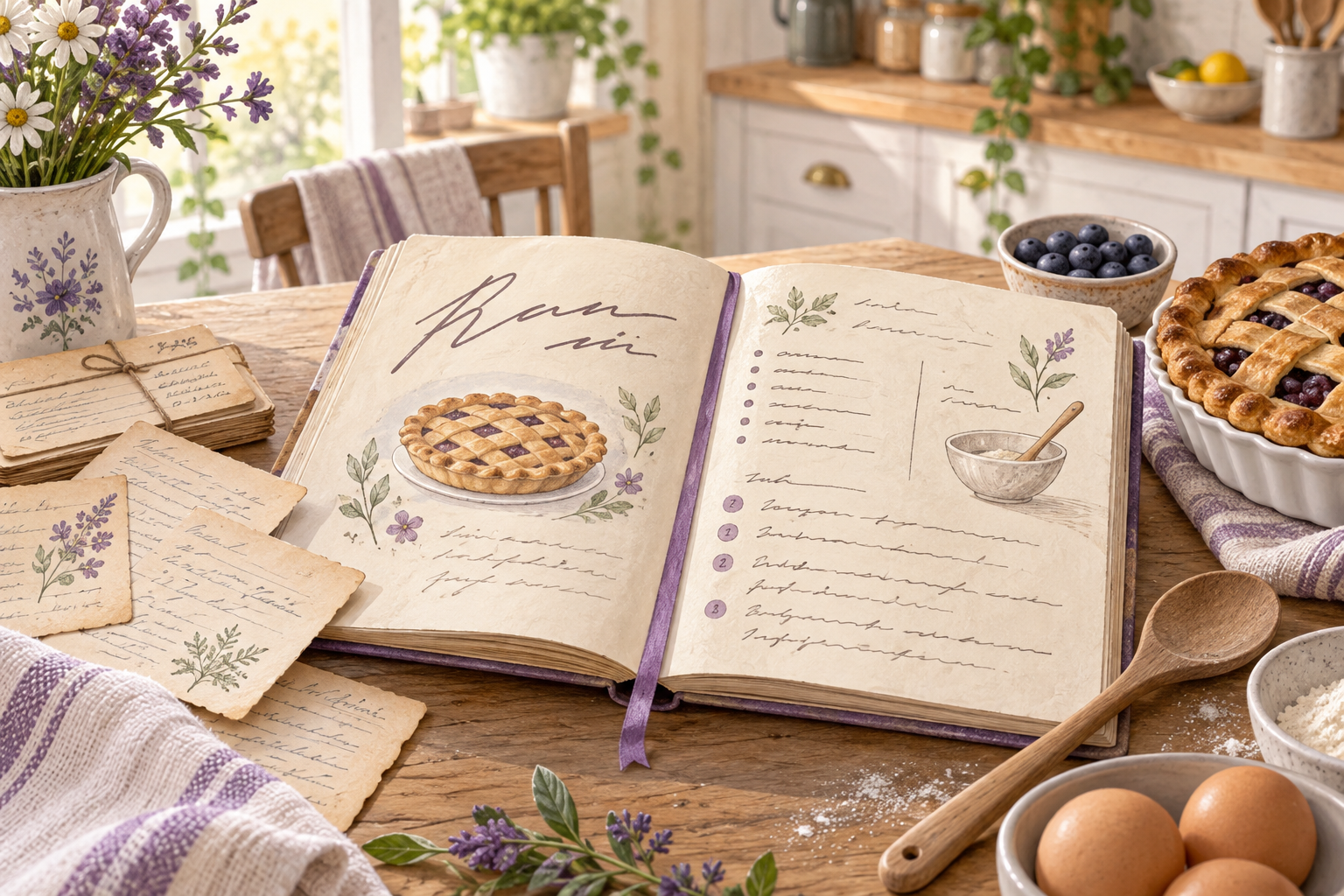
Семейная книга рецептов с рукописным шрифтом сохраняет характер оригинальных записей и помогает превратить разрозненные карточки в цельное издание. Чтобы рецепты оставались удобными, используйте почерк для названий и коротких заметок, а ингредиенты, количества и последовательность действий набирайте особенно ясно. Ниже — пошаговый план: от сбора материалов и подготовки букв до макета, проверки и печати.
Сначала определите, каким будет сборник
До рисования букв решите, что именно должна делать книга. Это архив семейных рецептов, который читают за кухонным столом, подарок к юбилею, небольшой тираж для родственников или файл, который будут пополнять со временем? От ответа зависят формат, объём, способ переплёта и степень точности при переносе старых записей. Подарочному изданию можно дать больше воздуха и фотографий; рабочей кухонной книге важнее крупные цифры, прочная обложка и страницы, которые удобно раскрыть.
Соберите рецепты из тетрадей, карточек, сообщений и устных рассказов. Для каждого запишите название, автора, ингредиенты, количество порций, температуру, длительность и шаги. Не исправляйте необычные семейные формулировки молча: отметьте, где запись расшифрована, где добавлено пояснение, а где значение нужно уточнить у автора. Так книга сохранит голос семьи, но не заставит читателя угадывать, что имелось в виду.
Почерк как источник, а не декоративный эффект
Выберите человека, чей почерк будет основой визуального образа: автора большинства рецептов, старшего родственника или нескольких членов семьи. Если рукописей много, сравните одинаковые слова и буквы на разных карточках. Почерк обычно меняется от скорости и инструмента, поэтому сначала решите, нужно ли воспроизвести конкретные особенности письма или создать аккуратный шрифт по мотивам почерка. Во втором случае можно сохранить характерные формы, но выровнять ширину, наклон и высоту знаков, чтобы набор выглядел последовательным.
Сканируйте или фотографируйте записи при ровном освещении, без теней, бликов и перспективного искажения. Сохраняйте оригиналы отдельно, а копии подписывайте понятными именами. Для оцифровки почерка подготовьте полный набор символов, который действительно нужен тексту: русские буквы, ё, прописные и строчные формы, цифры, знаки препинания, тире, скобки, дробную черту и единицы измерения. Рецепты часто содержат числа, поэтому цифры и пунктуация здесь не второстепенная часть набора.
Практичный компромисс: рукописным может быть заголовок рецепта или короткая приписка на полях, а основной текст лучше оставить нейтральным и ясным.
Разделите роли шрифтов
Не обязательно превращать весь сборник в набор одним рукописным шрифтом. Письменный стиль хорошо передаёт личное обращение, но длинные абзацы и плотные списки в нём сложнее быстро просматривать. Назначьте рукописной гарнитуре ограниченную роль: название книги, имя автора рецепта, заголовки, короткие семейные истории или цитаты с карточек. Для основного текста выберите спокойный шрифт с различимыми буквами и цифрами.
Сочетание должно поддерживать иерархию. Название рецепта заметно крупнее; строка с порциями, временем и температурой короткая и собранная; ингредиенты оформлены единообразно; шаги имеют ясную нумерацию. Если рукописный шрифт сильно наклонён или украшен соединениями, не ставьте его рядом с другим выразительным курсивом. Нейтральный прямой шрифт даст буквам пространство и поможет считывать смысл.
- Рукописный шрифт — для названия, подписи автора или короткого воспоминания.
- Нейтральный шрифт — для ингредиентов, количеств, температуры и инструкции.
- Полужирное или цветовое выделение — для одного-двух повторяющихся элементов, например времени приготовления.
Проверьте читаемость на настоящих рецептах
Пробный набор нужен до того, как вы оформите все страницы. Возьмите несколько фрагментов с разными задачами: рецепт с коротким названием, длинный список ингредиентов, дробные количества, несколько шагов, слова с похожими буквами и рецепт, где есть температура и время. Посмотрите на печатный лист в том размере, в котором книга будет использоваться. Уменьшенная страница на мониторе может скрыть слипшиеся соединения, неразличимые цифры или слишком тесные строки.
Особенно внимательно проверьте пары знаков, которые легко спутать в рукописном рисунке: и/й, ш/щ, л/м, ь/ъ, 0/О, 1/л и 3/з. Убедитесь, что буквы не касаются соседних строк, а цифры в количествах не теряют форму при печати. Проверьте тире и запятые: в списке продуктов маленький знак может поменять смысл записи. Если шрифт создаётся по почерку, просмотрите варианты соединения букв и добавьте альтернативные формы лишь там, где они делают набор естественнее.
Соберите страницу, которой удобно пользоваться на кухне
Удобство рецепта зависит не только от шрифта. Разбейте страницу на повторяющиеся зоны: название, короткая справка, ингредиенты, способ приготовления и личная заметка. Не прячьте время и количество порций в длинном вступлении. Слова «по вкусу» или «до готовности» можно сохранить, если они принадлежат исходнику, но полезно добавить проверяемые ориентиры, если автор рецепта может их подтвердить. Сохраняйте редакторские добавления отдельно от слов автора, чтобы семейная история не стала выглядеть как дословная запись.
Подумайте о сценарии готовки: книгу кладут на стол, открывают одной рукой, быстро ищут продукт и возвращаются к шагу. Для этого не ставьте длинную историю между каждым действием, не используйте декоративный шрифт для всего списка и оставляйте свободное место вокруг текста. Если есть фотографии блюд, не позволяйте им уменьшать область инструкции до нескольких тесных строк. Контраст текста и фона должен оставаться достаточным и на бумаге, и при чтении цифровой копии.
Пошаговый процесс подготовки макета
1. Отредактируйте расшифровку
Перенесите записи в таблицу или текстовый документ и присвойте каждому рецепту постоянное название. Уточните орфографию, но сохраните голос автора в примечаниях. Для неоднозначной меры или пропущенного шага оставьте пометку для проверки, а не подставляйте догадку. Сверьте список рецептов с оригиналами, чтобы не потерять оборот карточки или приписку на полях.
2. Составьте типовую страницу
Оформите один рецепт с самым длинным списком и самым длинным способом приготовления. Он покажет, хватает ли места в выбранном формате. Настройте стили заголовка, параметров, ингредиентов, шагов и заметок; затем примените их ко всему сборнику. Стили помогут держать единый ритм и упростят общие изменения.
3. Подготовьте рукописные формы
Если вы создаёте собственный шрифт, начните с частых букв, прописей, цифр и нужной пунктуации. Сравните повторяющиеся символы между собой, проверьте интервалы и соединения в словах из книги. Не исправляйте каждую неровность: небольшая естественная разница сохраняет почерк, а технические сбои вроде скачущей базовой линии и случайных наложений мешают чтению. Протестируйте файл шрифта в той программе, где будете собирать макет.
4. Проверьте длинные и трудные фрагменты
Наберите целиком страницу с объёмным рецептом, а не только красивое название. Проверьте переносы, русские кавычки, дроби, сокращения и специальные символы. Попросите другого человека прочитать количество и шаги без подсказок. Незнакомый читатель быстрее заметит места, которые автору кажутся очевидными лишь потому, что он знает рецепт наизусть.
5. Сделайте печатную пробу
Распечатайте несколько страниц в финальном масштабе на обычной бумаге и, если планируется цвет, также проверьте оттенки. Посмотрите на страницу при кухонном освещении, пролистайте её и отметьте, где взгляд теряется. Исправьте поля, размер основного текста, расстояние между шагами и заметность количеств. Затем перечитайте содержание и сравните ключевые места с оригинальными карточками.
Чеклист перед печатью
- Все рецепты сверены с источниками, включая обороты карточек и приписки.
- Количество, единицы, температура и время набраны без пропусков и расхождений.
- Назначение рукописного шрифта ограничено заголовками и короткими личными фрагментами.
- Цифры и похожие кириллические буквы различимы в печатном размере.
- Длинный рецепт помещается на странице без тесных строк и мелкого текста.
- Пробная печать просмотрена человеком, который не переписывал исходные карточки.
- В файле для печати использованы шрифты с подходящей лицензией и корректно встроенные или подготовленные к передаче.
Ошибки, которые делают книгу менее удобной
Рукописным набрано всё подряд
Сплошной рукописный текст может красиво смотреться на обложке, но быстро утомляет при поиске конкретной цифры или действия. Оставьте выразительному почерку роль акцента; длинные описания и списки наберите нейтральным шрифтом.
Макет проверен только на экране
Масштабирование и подсветка дисплея скрывают проблемы, заметные на бумаге. Маленькие цифры, тонкие штрихи и тесные строки могут потеряться в реальном размере. Для семейной книги пробная распечатка — часть редакторской проверки, а не необязательная отделка.
Угадываются меры и сокращения
Фразы «стакан муки» или «немного масла» могут быть понятны семье, но полезно выяснить, какой именно объём имел в виду автор. Если ответа нет, сохраните исходную запись и обозначьте неопределённость редакторской заметкой. Не выдавайте предположение за проверенный ингредиент или точную пропорцию.
Декоративные детали конкурируют с инструкцией
Рамки, орнаменты, фотографии и цветные метки уместны, когда они помогают ориентироваться. Если на странице одновременно несколько акцентов, взгляд перестаёт понимать, что важнее. Уберите украшения, которые не несут семейного или навигационного смысла, и проверьте, что название, список и шаги читаются в правильном порядке.
Можно ли набрать весь рецепт почерком автора?
Можно, если почерк достаточно разборчив и объём текста короткий. Для полноценной инструкции обычно удобнее оставить рукописными заголовок и личную заметку, а список продуктов и шаги набрать ясным шрифтом. Решение проверьте на распечатанной странице, а не только на экране.
Нужно ли создавать шрифт из одной карточки?
Одна карточка помогает передать стиль, но редко содержит все буквы, цифры и знаки. При подготовке собственного шрифта соберите несколько образцов и проверьте, какие символы отсутствуют. Если задача — сохранить оригинал, можно поместить скан карточки как изображение, а расшифровку дать рядом.
Как показать несколько авторов рецептов?
Сначала определите, действительно ли читателю важно различать авторов. Если да, используйте подписи, небольшие портреты или отдельные короткие пометки, сохраняя единый основной набор шрифтов. Не стоит смешивать несколько рукописных гарнитур в каждом рецепте: это усложнит навигацию и может превратить книгу в набор несвязанных страниц.
Что делать с неразборчивой записью?
Попросите автора или родственника, который знает рецепт, прочитать спорное место. Сверьте похожие карточки и привычные меры, но не исправляйте догадку без отметки. Если восстановить слово невозможно, сохраните фрагмент как есть и добавьте редакторское примечание, чтобы читатель понимал, где остаётся вопрос.
Подойдёт ли рукописный шрифт для ингредиентов?
Он может подойти для короткого перечня крупным кеглем, если буквы и цифры хорошо различаются. Но сочетание количества, сокращения и названия продукта требует точного распознавания. Проверяйте особенно дробные меры, сокращения и похожие знаки; при малейшем сомнении используйте нейтральный шрифт.
Какой формат страницы выбрать?
Выбирайте его по объёму рецептов, размеру переплёта и тому, как книгу будут держать. Сначала сделайте макет самой длинной страницы и напечатайте его в предполагаемом размере. Формат должен оставлять достаточно места для чтения и заметок, а не подгонять весь текст к красивой обложке.
Можно ли добавить старые фотографии и сканы?
Да. Скан рукописного оригинала добавит подлинности, а фотография готового блюда поможет узнать рецепт. Подпишите изображения, проверьте качество и оставьте рядом расшифрованный текст, если читателю нужно следовать инструкции. Уточните согласие родственников на публикацию личных записей и фотографий в тираже за пределами семьи.
Как сохранить возможность дополнять сборник?
Храните исходные сканы отдельно от макета, ведите редактируемый файл с рецептами и используйте единые стили страниц. Для будущих добавлений запишите правила: порядок разделов, способ записи времени и мер, оформление имени автора и роли рукописного шрифта. Это позволит сохранить общий вид, даже если книгу будут собирать заново.